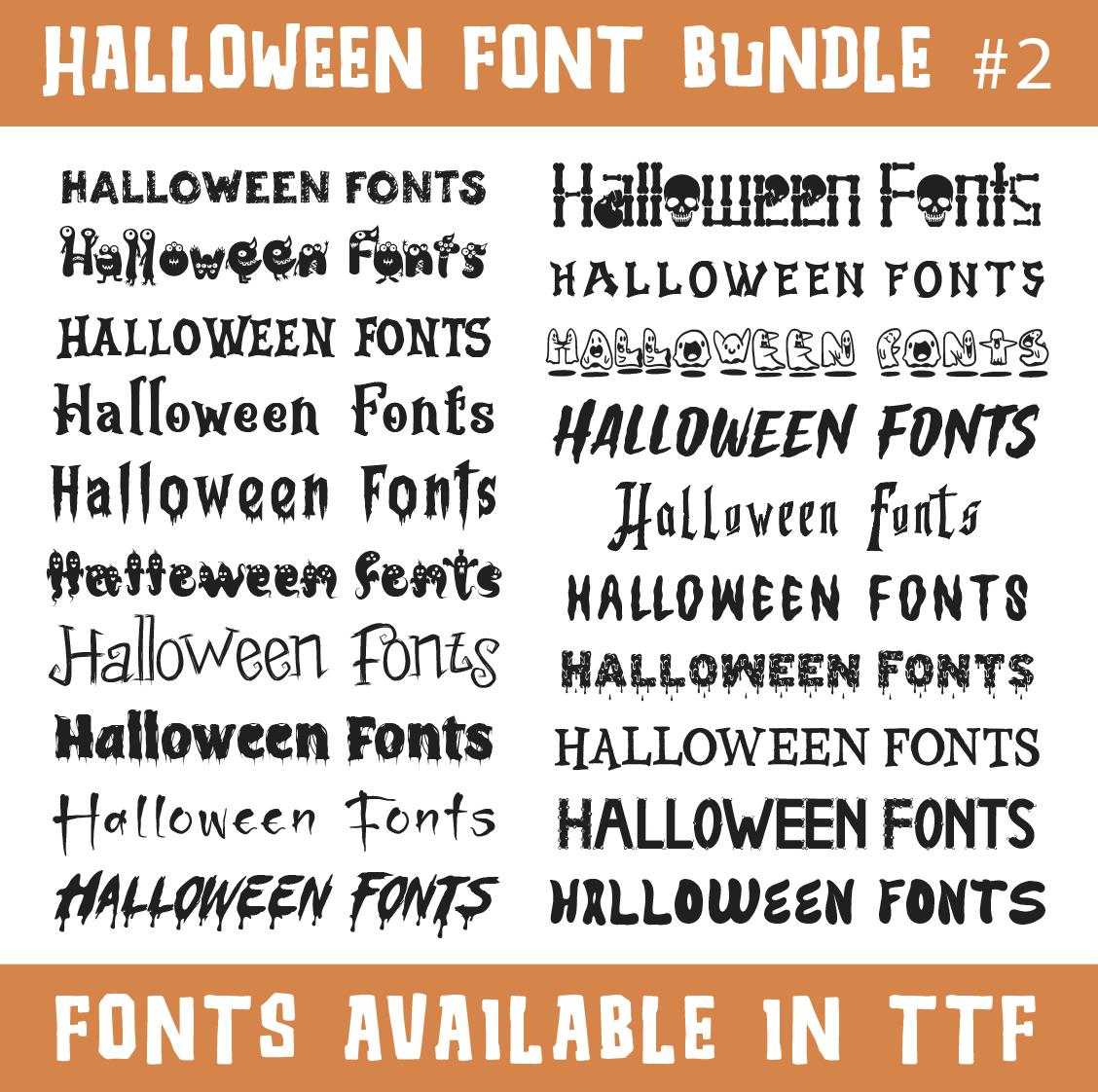
Bộ font chữ Halloween Fonts là sự lựa chọn hoàn hảo để tạo nên những sản phẩm độc đáo, ấn tượng, từ thiệp mời, poster, banner cho đến những thiết kế đồ họa phức tạp hơn. Phong cách thiết kế lấy cảm hứng từ hình ảnh những bộ xương cổ đại và những con tàu cướp biển ma quái, nhưng vẫn giữ được nét vui nhộn, nhẹ nhàng, phù hợp với cả những thiết kế mang tính giải trí cao. Mỗi font chữ đều được trau chuốt kỹ lưỡng, mang đến sự đa dạng về kiểu dáng, từ chữ in hoa đến chữ thường, đáp ứng mọi nhu cầu sáng tạo của người dùng.
Ứng Dụng Đa Dạng Của Bộ Font Chữ Halloween